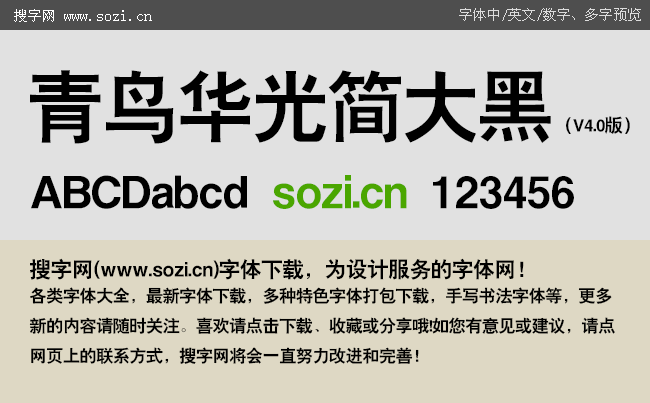
青鳥(niǎo)華光簡(jiǎn)大黑
搜字網(wǎng)提供一款青鳥(niǎo)華光簡(jiǎn)大黑字體下載,青鳥(niǎo)華光簡(jiǎn)大黑是一款粗黑體字體,該字體端正大方,清晰醒目,整體風(fēng)格出色,適用于廣告設(shè)計(jì)、名片設(shè)計(jì)、包裝印刷、產(chǎn)品設(shè)計(jì)等應(yīng)用。